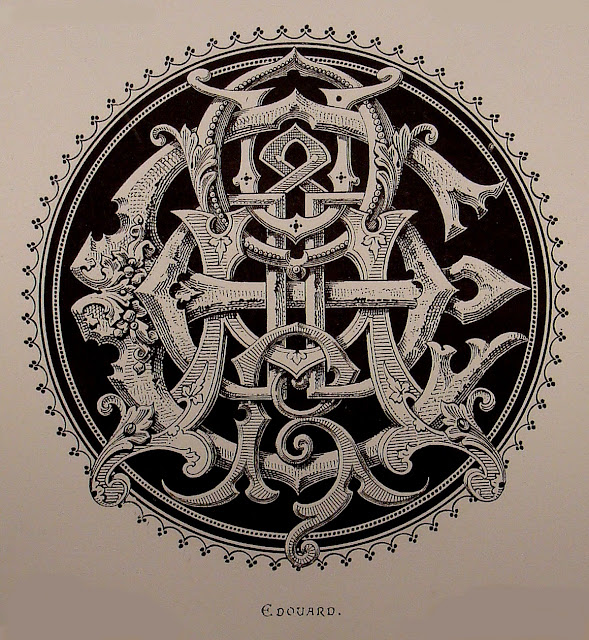
DEMENGEOT, Ch. "DICTIONNAIRE DE CHIFFRE-MONOGRAMMES DANS LES STYLESET RENAISSANCE ET COURONNES NOBILIAIRES UNIVERSELLES."
Paris: Demengeot- Juliot, 1881, 2 Volúmenes.
- Vol. I: Gran Folio (33x44), Una hoja con la primera pre-portada con título y dedicatoria del autor manuscrita a:Aglaïus Bouvenne, detrás un monograma, una hoja con un Heliograbado de Dujardin del retrato de Demengeot, una hoja en blanco, una hoja repitiendo la 1ª portada igual que el primer folio, una hoja con la portada a dos tintas, rojo y negro, tres hojas numeradas en romanos, 98 páginas de la primera parte, 116 páginas de la segunda parte, 1 hoja con la justificación de la tirada, una hoja en blanco.
- Vol. II: Gran Folio (33x 44), Atlas de láminas, la portada con el famoso Monograma de todo el alfabeto grabado por el autor y colección de 33 láminas con diferentes monogramas y coronas heráldicas.
Sin duda es un libro en mayúsculas y el trabajo y diseño de los monogramas lo sitúan en la cumbre de esta especialidad.
LETRA E
| Lámina nº9, Demengeot -1881 |
| Lámina nº10, Demengeot -1881 |
| E-E |
E-F
| Monograma de EDOUARD |
E-G
E-H |
| E-I |
| E-J |
| E-K |
| E-L |
E-L
| Monograma de ELISABETH |
| E-M |
| E-N |
| E-O |
| E-P |
| E-Q |
|
| E-Q |
|
| E-R |
|
| E-S |
|
| E-T |
|
| E.T |
|
| E-U |
|
| E-U |
|
| E-V |
|
| E-W |
LETRA F